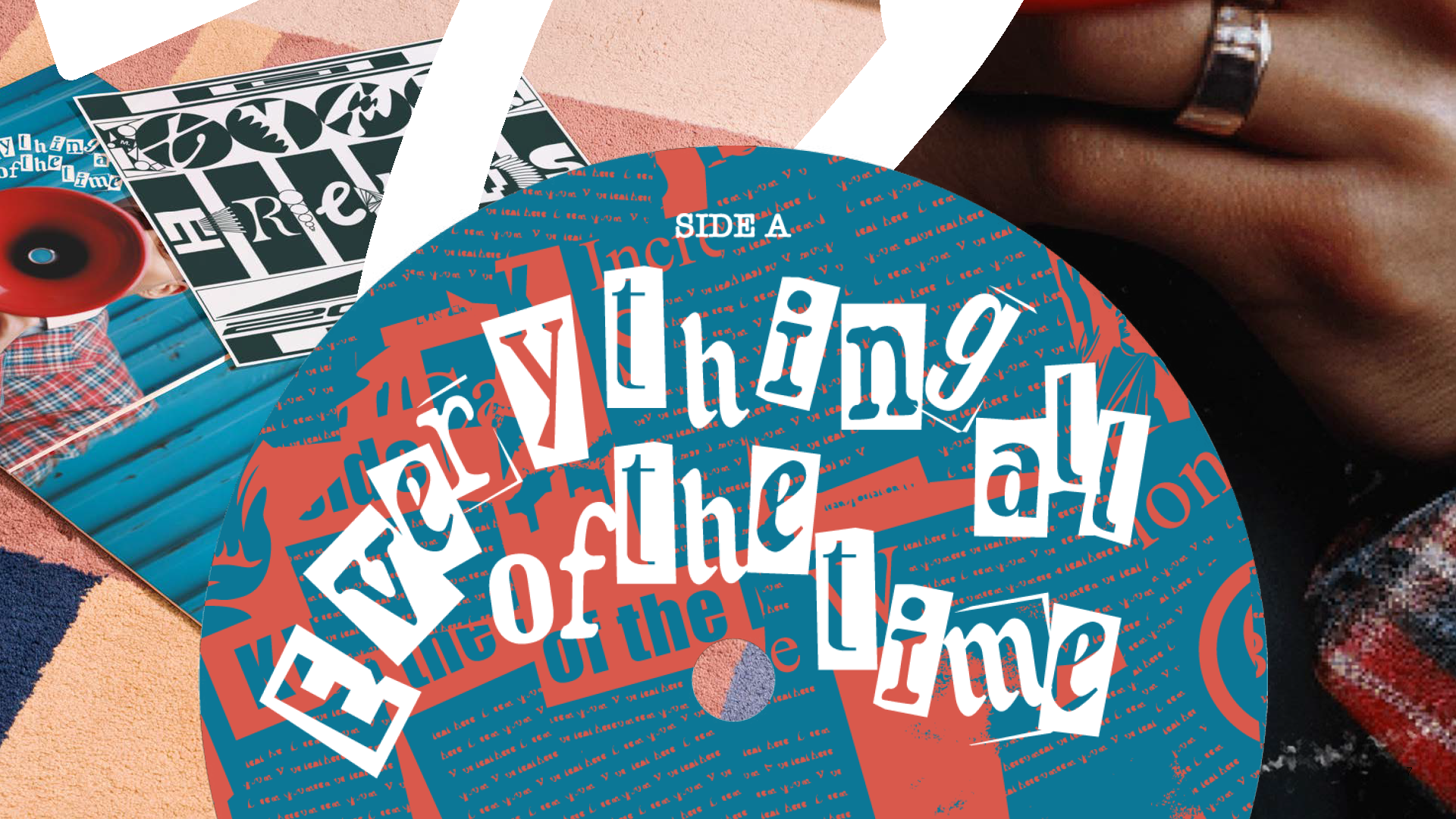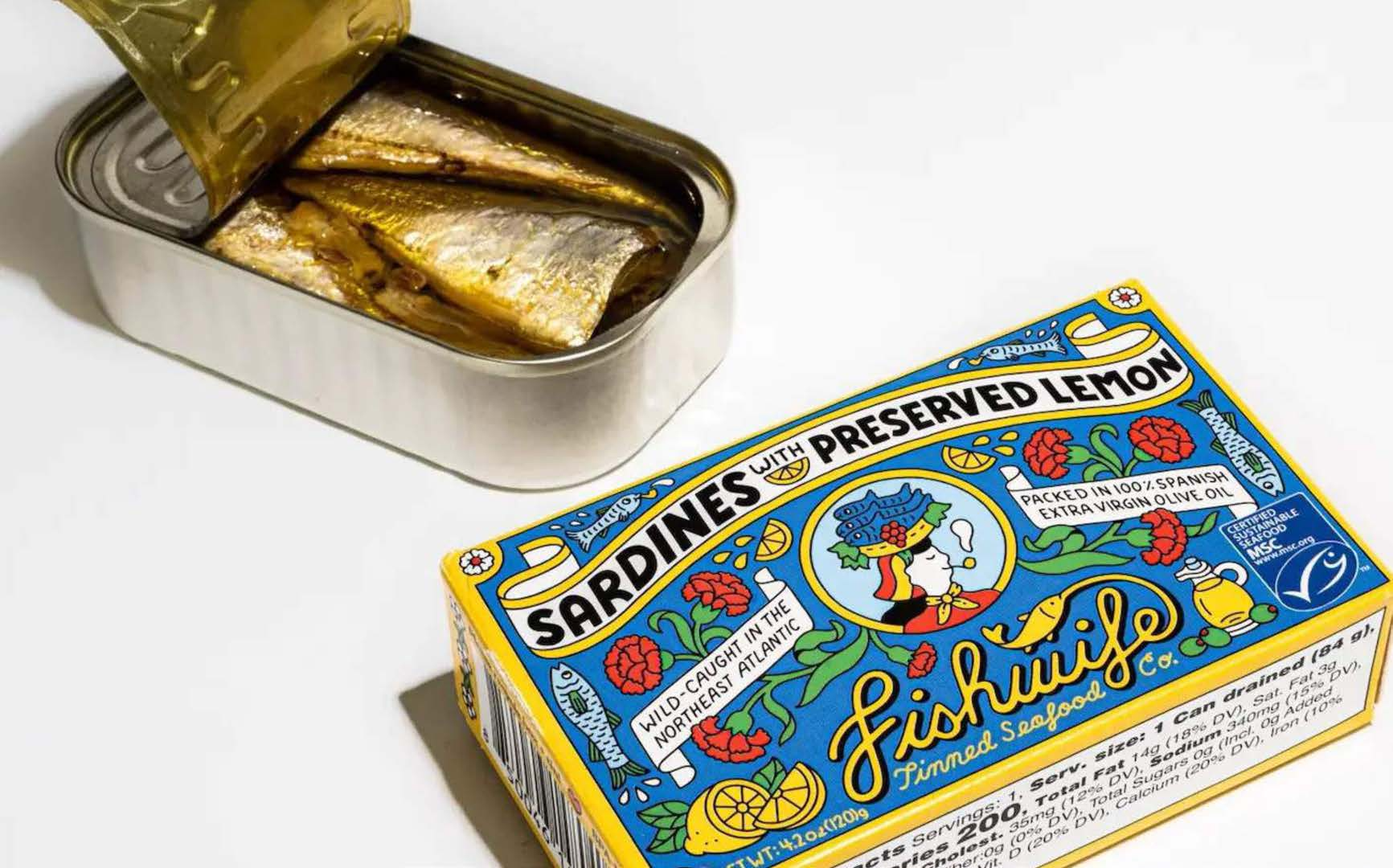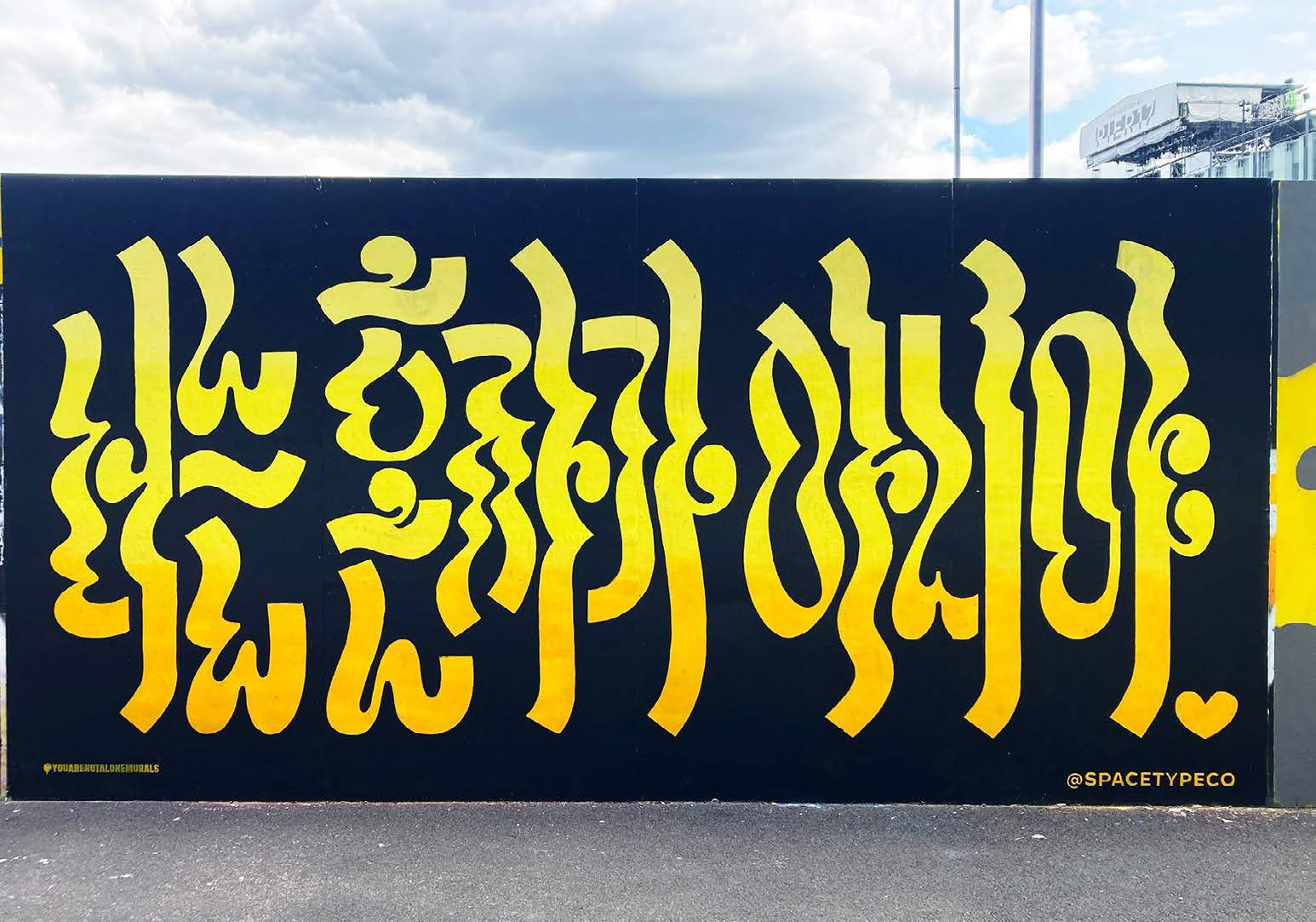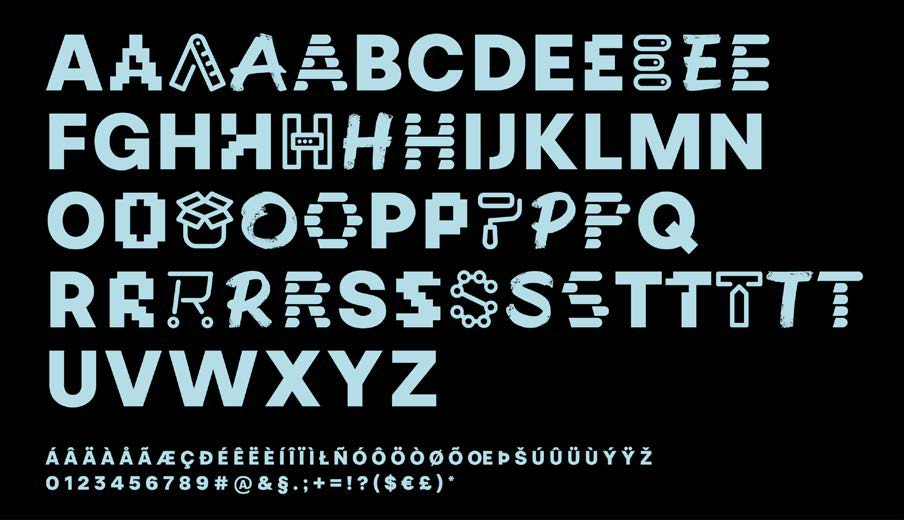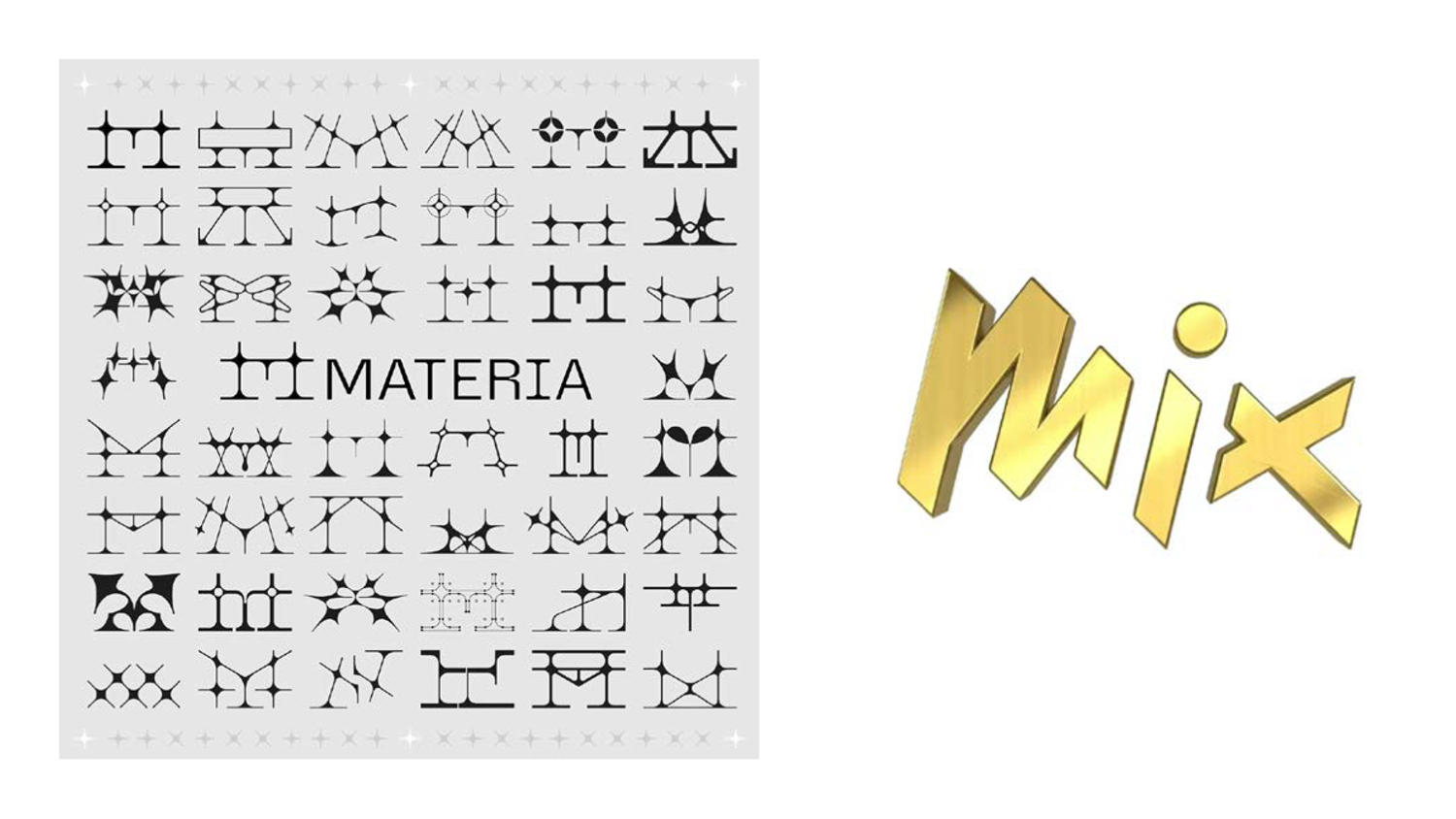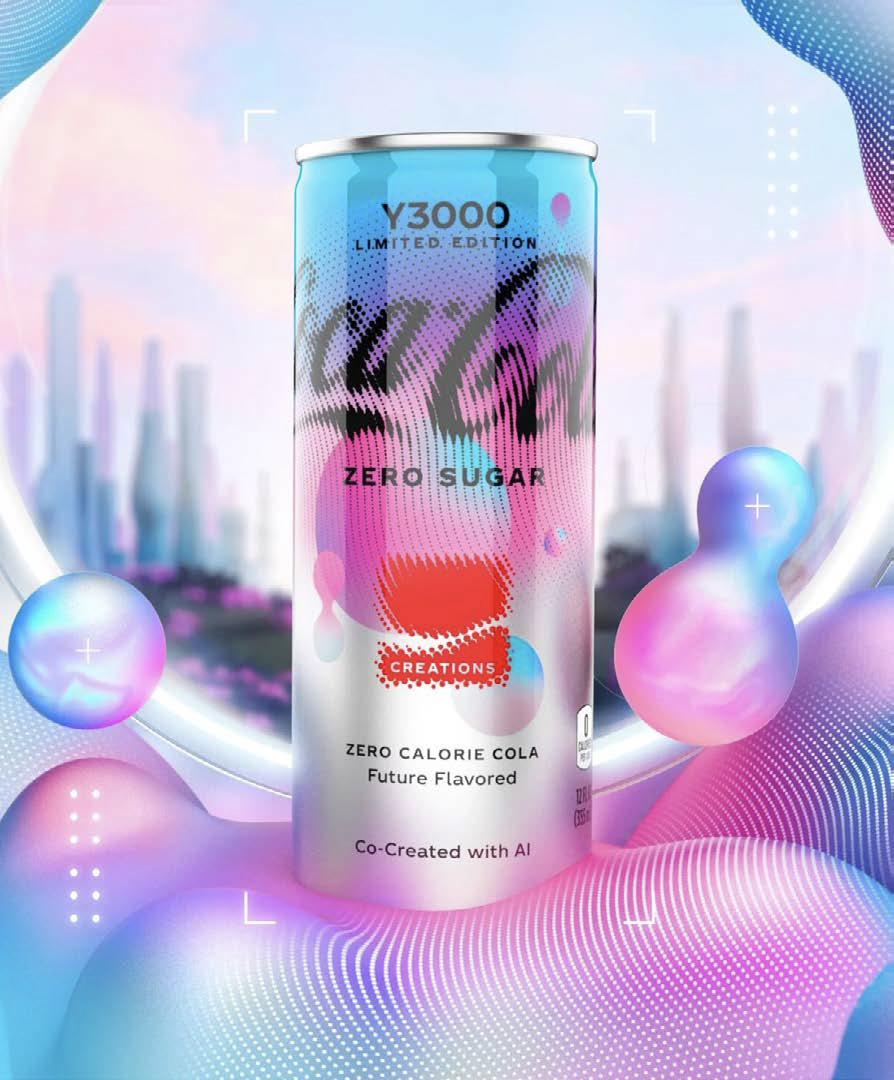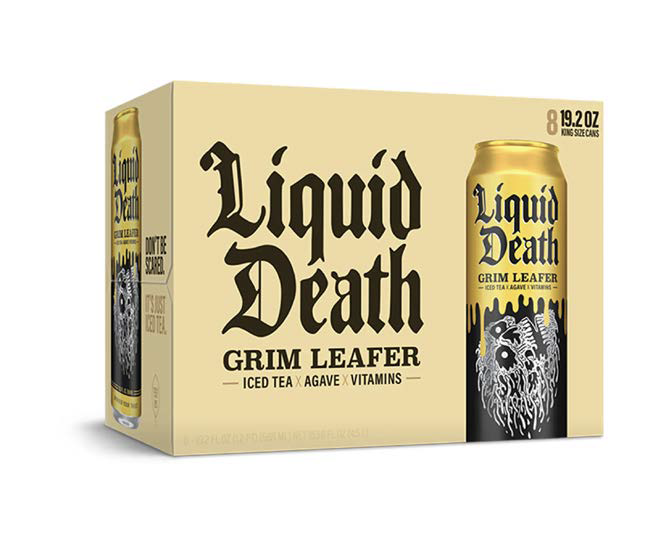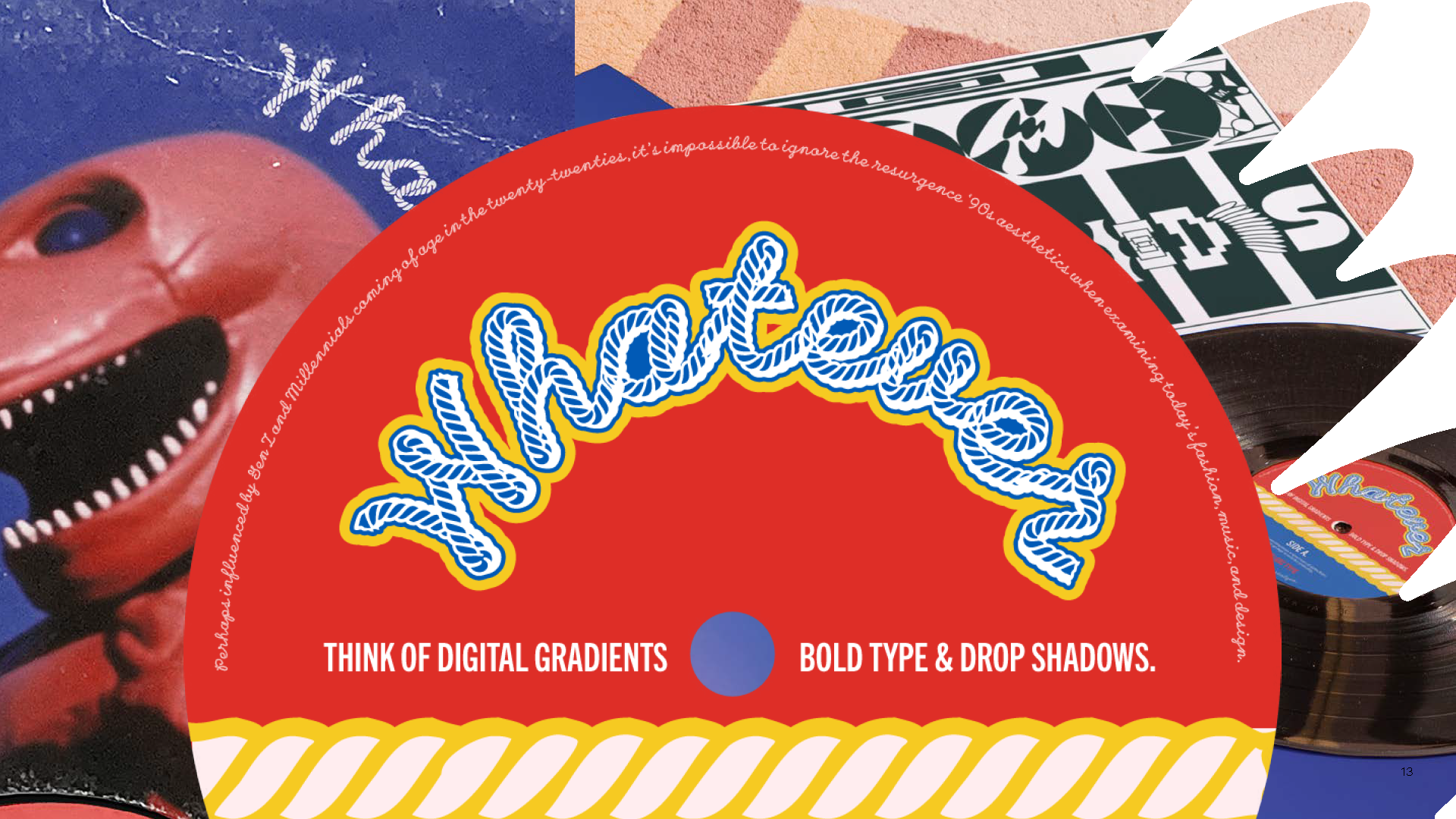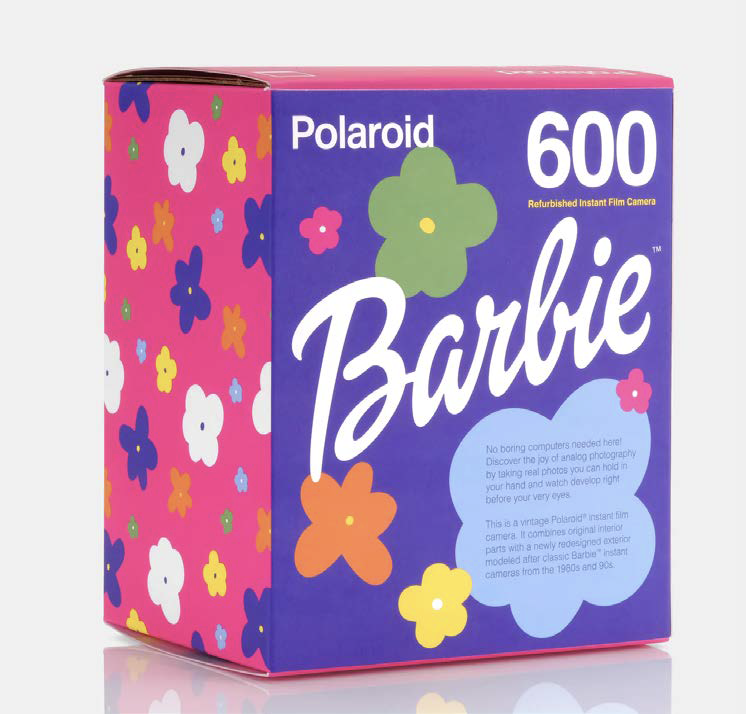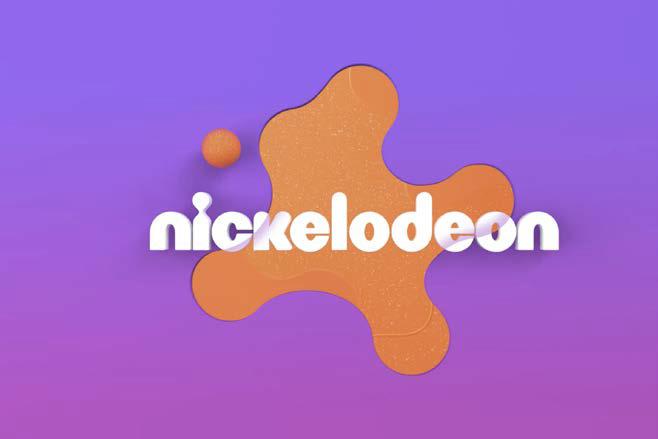
2024 新春之际,蒙纳面向全球正式发布《2024 年度字体趋势报告》。
本年度报告紧随过去一年里 AI 技术与设计的碰撞视角,亦关照复古美学与传统元素的回潮,捕捉错综复杂的当下,品牌与创意人士不约而同的表达诉求。
10 张由 Midjourney AI 共创的黑胶唱片封面,诠释 10 大字体趋势;60+ 全球年度先锋设计作品,涵盖从独立工作室到知名设计机构,从新锐品牌到老牌企业,令人惊艳的设计实践和应用场景。
黑胶唱片的视觉语言已经广受大众认可,而今年的趋势报告灵感也正源于此。在黑胶唱片封套经典的设计风格基础之上,这份趋势报告还融入了“摇滚”、“重金属”、“嘻哈”、“乡村”和“电子”等大众熟悉的音乐流派,并与字体中的不同风格联系起来。今年的趋势报告将涵盖更广泛的受众,提炼 10 个字体趋势,并辅以相关的研究与洞察详细阐述。
此次报告将字体置于音乐这一通用的场景,在创意人士和大众之间构建桥梁。在视觉上,我们借用熟悉的音乐流派,与不同的字体趋势建立视觉上的关联,通过丰富的配图,体现趋势背后的文化动因。
1 包罗万象 EVERYTHINGALLOFTHETIME.
如果说字体诉说了关乎当下世界的信息,那么此趋势便是一气呵成地反映了生活的方方面面。这一标题灵感来源于美国喜剧演员、音乐家和电影制片人 Bo Burnham 颇具调侃语调的歌曲《欢迎来到互联网》。这首歌以喜剧的方式展现了现代场景下的信息爆炸,以及令人沉溺却也兴奋的新兴网络世界。
Fishwife 是一个女性创办的食品品牌,专注于为消费者提供来源更有保障的优质即食鱼罐头。最近,该品牌推出了一款腌柠檬辣沙丁鱼新品罐头,其包装完美诠释了“包罗万象”的极致美学。设计师 Danny Miller 融合矢量插画、复古摄影、活泼色调、时髦字母与温情字体,创造出天马行空的包装设计,赋予罐头“秀色可餐”的视觉魅力。
Lynne Yun 为公共艺术项目“你并不孤单”创作了一幅壁画,该项目旨在激发人们对心理健康的关注。Lynne 用富有表现力的韩文字母进行绘制,向途经曼哈顿下城海港的韩语使用者们传递友好之意。壁画以鲜明的黄色、橙色和粉色为主色调,曲线优美,充满趣味性与实验性,并加以 Beatriz Lozano 制作的三维和图像识别 AR 扩展,使得色彩能够如键盘按键那样交替变换。
法国先锋设计公司 Lonsdale 为欧洲和拉丁美洲领先的开源电子商务解决方案提供商 Parisian Prestashop 设计了品牌形象,并以定制字体 Prestafont 为核心。新字体涵盖 4 款不同的字体家族,即像素字体、毛笔字体、图形字体以及装饰性无衬线体。这些字形基于核心的无衬线体演化而成,以反映 Parisian Prestashop 商家资源的丰富度及软件服务的自由度。每款字体风格都颇有意趣,混排时更是别开生面,与柔和淡雅的色彩相得益彰,展现字体排印的无限魅力。
如何才能真实地捕捉到物理空间的多面性?Materia(一家数字艺术画廊)和 Mix Brussels(一家集酒店、健身房、协同办公空间于一体的场所品牌)的徽标都以“包罗万象”的手法反映了空间的多面性。
总部位于巴黎的创意工作室 Golgotha 为 Materia 设计的徽标赋予了字母 M 48 种装饰变体。同样,Base Design 为 Mix 设计的形象也从 60 年代建筑中汲取灵感,以不同质感暗示 Mix 能够为用户提供多功能的空间。这两种非常规的设计方式都展示出设计师在探索徽标的极限 —— 既然标识可以包含多种元素,自然可以容纳更多表达。
在这一趋势中,还有两个饮料品牌案例值得一提。首先是拥有百年历史、广受认可的全球标杆性品牌可口可乐。可口可乐的最新限量版口味 Y3000 “能让人尝到未来”,因此团队利用 AIGC 共创包装设计,用流动的液点组成可口可乐标志性的斯宾塞体 logo,以“代表这颗星球未来的人类联系”。
在创意过程中借力 AI,是否能够比仅依靠人类创造出更惊艳的结果?你大概有自己的思考和回答,但同时也可以留意这样一个关键:这类案例不仅反映了某种设计趋势,也在启发更多相似实践。AI 所生成的复杂图案,也在推动设计师们创造更天马行空的作品。
相对于可口可乐,Liquid Death 是个更为新锐的罐装水品牌。从“MURDER YOUR THIRST”的标语到金属风格的骷髅头元素,这一品牌在营销和品牌塑造上都采用了自由不羁的风格。创意副总裁 Andy Pearson 表示:“Liquid Death 是许多有趣事物的混合体,比如重型音乐、黑色幽默、讽刺艺术等等。”还有什么比这更为“包罗万象”呢?
2 随心所欲 Whatever.
第二个字体流行趋势源于 90 年代的怀旧风潮,同“包罗万象”一样,该趋势涵盖了从垃圾摇滚到多彩像素等各种风格。渐变色彩、粗体大字、字体阴影……或许是受到 Z 世代及“千禧一代”的影响,在审视当今的时尚、音乐和设计时,我们无法忽视 90 年代美学的复苏。
2023 年 7 月上映的《芭比》,为这一年增添了许多桃红色与霓虹灯的 90 年代时尚元素。无数品牌与芭比跨界合作,希望借助这部年度票房大片获得热度。来自密尔沃基的产品设计工作室 Retrospekt 推出了芭比主题的宝丽来 600 拍立得相机,汲取上世纪 80 和 90 年代标志性的芭比元素,顺应了千禧一代的怀旧浪潮,为拍立得相机本身注入了更多的乐趣。
设计工作室 Roger 为尼克国际儿童频道更新的徽标,便是以理解孩子们的奇思妙想为核心概念,通过全新的形状和色彩,重塑标志性的粘液标志。该徽标采用了 ROC Grotesk 字体,并与 Neue Plak 字体搭配,在俏皮和凝练之间取得了平衡。
另一个深受孩子们喜爱的品牌是 Jell-O 果冻,知名品牌设计公司 Brand Opus 帮助其进行了十年来的首次品牌重塑。此次视觉更新以字体为核心,使用了圆润厚重的无衬线体,并刻意将较宽的字体 O 略微抬高,旨在以前卫的字体风格,唤起消费者的愉悦联想。改版后的徽标带有白色阴影,应用在带有鲜明卡通图案的包装上,也格外清晰。
英国伦敦知名广告公司 VCCP 与裸眼立体画出版商 Magic Eye Inc® 合作,通过创作一系列神秘的视错觉艺术品,帮助酸奶品牌 Müller Corner 焕发生机。“从时尚服鞋,到 Instagram 滤镜和 Tiktok 趋势,90 年代美学正在风靡。”Müller 战略和营销总监 Toby Bevans 表示,“消费者调研启发我们,重新推出过去广受青睐和怀念的密西西比棉花糖派口味,或许能帮助品牌在挖掘传统方面大有作为。”
是什么让“随心所欲”成为了甜点品牌的流行趋势?也许是我们从甜食中所体验到的舒适,让我们回想起孩童般的快乐与温暖。位于纽约的设计工作室 Safari Sundays 邀请字体厂商 Grilli Type 协助开发了一款名为 SWERVE 的标题字体,为 7-11 便利店的思乐冰(Slurpee,一款碎冰饮品)增添了新意。此外,它们还推出了吉祥物“Styles”,这个吉祥物由字母 S 组成,并与甜品的形状相匹配,从而彰显每个人心中所深藏的孩子气。霓虹色调、格纹图案、 全新标语……这些新鲜的声音帮助品牌与 Z 时代和千禧一代的年轻受众建立起更紧密的联系。
3 井然有序 SYSTM.
如果说“包罗万象”反映的是现代生活中的错综复杂,那么“井然有序“则回归结构、控制和精确,让人得以短暂喘息。
位于阿姆斯特丹的设计工作室 WONDERLAND 的执行创意总监 Martijn van der Does 将其称为“慢设计”。他表示:“我们由技术驱动的快节奏世界重视速度和效率,而慢设计则与之对抗,倡导一种更深思熟虑的方式。”它鼓励我们与使用的产品和居住的环境建立更深层次的联系,从而对抗快速消费文化。
在过去的几年中,模块化、机械化和工业化的字体变得更为温暖细腻。“井然有序“延续了该趋势,同时更强调“亲身参与”的理念。尽管设计字母有着既定方法,但本趋势所涵盖的设计实践,以更柔和的形式、更周到的考虑,增强了人性化因素。
“我们创造简单易安装的高级设计。”
阿姆斯特丹建筑产品制造商 Nown 的标语完全彰显了“井然有序”的精髓。该企业的视觉形象由巴黎设计公司 Brand Brothers 负责,采用了较宽的定制徽标,强调锐利而重复的角度,以及各段之间的连接细节,与他们生产制造的碳中和建筑产品相呼应。搭配的字体为 Lineto 的 Replica,且大多应用的是大写字母。
下面,让我们来看一看英国曼彻斯特博物馆更新后的南亚展厅。独立设计师 Sthuthi Ramesh 与字体厂商 Universal Thirst 合作设计了 SAG Stencil 字体,旨在捕捉从南亚到曼彻斯特沿途旅程的精髓。SAG Stencil 采用了模块化字体,横跨孟加拉文、天城文、古吉拉特文、果鲁穆奇文、拉丁文、泰米尔文和乌尔都文共七种文字。这款定制字体的灵感来源于古吉拉特活字印刷厂 1937 年的字体样张,以及在印度火车站发现的手工标牌,从而赋予展厅历史感和创造力。
另一个关于“井然有序”的案例或许会让你意想不到,来源于啤酒品牌 Molson Coors。芝加哥 DDB 广告公司为 Coors Light 设计的凉爽屋檐(chillboards)屡获殊荣,利用字体排印为佛罗里达州迈阿密的一个社区降温。团队邀请当地街头艺术家 Andaluz 协助设计了一款定制字体,在屋顶上使用了高反光的白色油漆涂上该标语,覆盖面积达 96%,从而帮助居民节省水电费,并提高对气候变化的认知。更酷的是,作为此次营销活动的一环,Molson Coors 还将送出 5000 加仑反光白漆。
接下来是耐克的 CURV Studios 字标案例,由著名广告公司 AKQA 设计,代表着创意的四个阶段,即准备、孵化、启示和验证。每个字母都被框定在气泡状的 4×4 网格中,在不同比例下都非常清晰。与之搭配的 swoosh 标志,灵感来源于耐克的创新文化,也被分割为 4 个部分,与创意的各个阶段匹配。
最后一个案例来自于平面设计工作室 Workbyworks 为街头服饰品牌 BONELESS 设计的标识,该品牌致力于为年轻一代提供高品质且价格合理的服饰。设计以宽比例的字母 B 为核心,采用 3×5 的灵活网格结构,为徽标和布局系统奠定了基础。
4 重塑结构 De-form.
这是一款举世惊艳的可变字体,抑或只是有些“变形”?如果将画面上所有可能的像素都填满,又会是什么效果?
不同于“井然有序”,“重塑结构”打破了字体的骨架,渴望占据更大的画面版块,将字体的可能性无限延展。这一趋势下的字体们在不同的状态间摇摆变形,既端正又柔软,却很少介于中庸状态,而是呈现强烈的视觉冲击力。
该趋势也正促使设计师们尝试过往几十年来不被提倡的变形方法。“重塑结构”的设计不再严格遵循字重平衡、宽度一致、字形比例,而是享受更多实验乐趣。
这一趋势是否是在对抗保守的同质化设计和过度简洁的技术美学?或许暗流涌动的全球文化和社会问题(如战争、政治极端主义、通货膨胀、罢工和生活成本问题)正在引发美学的反叛。设计师们是否潜意识中吸收了这些情绪,并反映到了作品中?也许我们需要打破因循守旧的规则,表达更多共同经历的当下。
设计工作室 Kiln 受委托为英国皇家电视学会(Royal Television Society)的剑桥大会设计标识,旨在突出学会“太多可看(Too Much to Watch)”的主题,同时避免让人感到悲观或焦虑。
徽标采用了色彩丰富、充满张力的气泡字母,字母排列紧密,仿佛在争夺着空间,与当下不断涌现的内容争抢着注意力相呼应。设计团队利用定制的渲染技术随机操纵字母形状,从而通过基于物理模拟的复杂动态设计增强了该效果。
美国服饰品牌 American Apparel 以其极简美学而闻名,与设计公司 LG2 Architecture 合作,在时尚展会中打造了类似博物馆的体验,以宣传其经典的 Black 2001 T 恤。参与者沿着引导路径进入一个离地 4 英尺,16 英尺高的黑色箱体;在里面,他们会体验 7 个展示经典 Black 2001 T 恤特性的装置。箱体表面的字体尺寸巨大,并拉伸扭曲到极端比例,视觉效果上却恰到好处、协调一致,与令人印象深刻的快闪展览形式相得益彰。
Detroit 是位于巴黎的一家创意机构,代表了一批国际人工智能艺术家,从事传播、新闻和文化领域的工作。徽标基于 Acumin Extra Condensed 字体,旨在强调“Detroit”这一机构名,以及人类和机器间的羁绊概念;结构的变形则是呈现了人工智能凭借其无限可能性而引起的眩晕感。
瑞典风景宜人的达拉纳地区,以旅游业以及铜矿开采、骑马、越野滑雪等传统行业而闻名;但该地区也是一些全球高科技企业的所在地,需要吸引年轻的员工。因此,斯德哥尔摩设计公司 Soderhavet 与 Placebrander 合作,为达拉纳地区打造全新品牌形象,突出发展前景。定制完成的标题字体,美学灵感源于丰富的文化要素,外形敦实而具张力,仅用一个字母或是一个单词,再加上遮罩图像,便能成为传达品牌故事的窗口。
设计工作室 &Form 为东京巨蛋城设计的徽标业采用了类似的思路,利用与大曲都市(Toshi Omagari)共同开发的定制软件,使可变字体可以在不同形状和颜色之间变化,从而展现该设施所提供服务的多样化。
全球知名的设计公司 Pentagram 为拥有 148 年历史的英国百货品牌 Liberty Fabrics 独家设计了包袋和围巾胶囊系列。为了传达其“毫不掩饰的古怪”的品牌理念,Pentagram 与字体公司 Colophon 合作定制了 Lasenby Sans 字体。这是一款人文主义字体,灵感提炼于 Liberty 悬挂于大马尔伯勒街入口处的招牌字样。设计团队利用这款字体玩转排版设计,将传统风格与现代技术相结合,创造出了大胆的万花筒纹样。
5 流动 Flux.
“流动”或许可以算作“重塑结构”下的细分类别之一,也是过去几年逐渐流行起来的趋势。无论是真正的动画还是仅从动态中获取灵感,“流动”都充满速度与活力。你或许还会发现利用人工智能创造动态和交互的字体。以下相关的创意项目都关乎品牌重塑,其中还包含了两个强调转变与速度的体育品牌。
首先是全球知名的设计公司 Pentagram 的另一个代表案例。他们与设计工作室 Nomad 和创意咨询公司 Heavenly 共同合作,为伦敦自然史博物馆进行品牌重塑,传达出力量与活力。升级后品牌形象的核心是从内向外扩散的环形字母,象征博物馆积极推动地球自然环保。定制字体 NHM Wallop 基于字体公司 Displaay Type 旗下的无衬线体 Wallop,也在排版中应用到了环状结构。设计团队制作了一个生成器,可以通过编码创建静态和动态输出,使任何与博物馆合作的设计者都能够轻松兼顾一致性和灵活性。
“这些元素能够运动、生长、扩展和变形,以动态的方式进行交流,为品牌注入令人难忘的活力。”
为加强与意大利城市的紧密联系,全球知名的品牌设计机构朗涛(Landor)协助意大利最重要的交响乐团之一 LaVerdi 进行品牌重塑,更名为“米兰交响乐团”,并从通感(synesthesia)这一概念中汲取灵感,定制了颇为前卫的字体 TUMB TUMB,构成徽标的核心。
“徽标能够根据乐团演奏的强度而变宽或变窄”,在视觉上回溯了 20 世纪早期艺术作品风格,为整个乐团形象注入了活力与能量。
现在让我们把目光从艺术转向游戏行业。英国创意公司 Uncommon 将热门足球游戏《FIFA》系列更名为《EA Sports FC》,并使用了全新的三角品牌标志,这一形状来源于游戏中玩家角色上方浮动的三角形。Uncommon 还与字体厂商 F37 合作,从两位传奇足球运动员约翰·克鲁伊夫(Johan Cruyff)和玛塔(Marta)身上汲取灵感,定制了两款字体。一款字体将克鲁伊夫的风格融入到字干的结构设计中,在三角形元素中加入了油墨陷阱(ink trap),而另一款字体则彰显了巴西足球运动员玛塔的风格和天赋。
设计机构 DesignStudio 在重塑广受欢迎的德国多特蒙德足球俱乐部(Borussia Dortmund,简称 BVB)品牌形象时,采用了现代与经典兼顾的方法,在尊重其丰富传统的同时,还引入了富有速度感的可变字体和标志。团队与字体公司 Blaze Type 合作,设计了一款定制字体,与多特蒙德主场西格纳尔·伊杜纳公园球场站台 34º 锐角相呼应。可变字体的形式彰显了多特蒙德厚积薄发的体育精神,标题字体增加了独特的“强度字符”,并与功能性的正文字体相平衡。升级后的品牌形象捕捉到了 BVB 的精神根源,与球队标志性的黑黄色调相搭配,传达了球队强大的生命力和联结力。
众筹贷款平台 Bankers 横跨半个地球,进入日本市场,并在大约 30 个月的时间里累计获得 200 亿日元的投资,堪称“业内最快”。为了与其快速发展相匹配,Bankers 在东京地区火车站的品牌广告中采用了质感强烈、渐变丰富的插图,并搭配看起来像是用软头钢笔快速书写而成的字体,传达出惊艳与快速的能量,彰显品牌活力。
6 怪诞 Quirk.
所谓“怪诞”(Quirk),顾名思义,指的是利用一些显眼特征来吸引客户眼球的字体。毕竟,品牌推广就是需要一定的激进思考:愿意尝试一些意想不到的事物,特立独行。然而,这种“与众不同”似乎与客户的“舒适度”存在一些冲突。 这种冲突,催生了许多“怪诞”创新:利用一些别具匠心小设计, 在符合整体视觉规范的前提下,带来一丝松弛感。这一趋势,强调的是“舒适度”和“视觉张力”之间的平衡,那些小小的怪诞设计,像是藏在普通的无衬线背后,对你抛媚眼。
廉价航空公司 Scott 's Cheap Flights 更名为 Going 之后,DesignStudio 为其重新设计了字标,使其更具表现力和趣味性,也彰显了 Going 在旅游行业的重要地位。新的字标呼应了旅途中的意外之喜,字母 G 顶部的小圈让笔画方向自然向下,象征品牌一直秉承的低价理念和极致性价比。字标中字母皆以斜体呈现,字母 G 以箭头收尾,更加凸显了力量感。配色的灵感源于全球的生物多样性,箭头还模拟了地球自转方向,也寓意着跨越长距离的旅途。充满冒险精神与好奇心的旅程,这也是 Going 的愿景。
“用一首特别定制的歌曲,点亮别人的世界”,这是 Songlit 平台的理念。其品牌的定制字体也体现了音乐本身流动顺滑的意象。Songlit 的品牌设计由 Australian Studio Work 完成,结合了 Dinamo 字体公司的 Maxi Plus Variable 和 Repro 字体。新的品牌包含了大量的插画元素,色彩明亮,体现了平台无尽的定制化可能性。
Wisl 被称为“本地体育引擎”,用户可以找到有共同兴趣的运动搭档。来自立陶宛的设计公司 andstudio 为其定制了字标,其中的字母 W 成为了品牌代表性的元素,彰显玩趣与亲和力。手绘插图、图标、弹力球,让品牌形象鲜活有力,与运动的激情产生关联。
宠物护理品牌 FLOOF 的徽标和品牌形象由纽约创意机构 SMAKK 完成,其设计运用了类似的手法。 FLOOF 旨在为狗狗提供从头到尾的护理。徽标中字母 L 的设计带着些许俏皮,品牌使用的正文字体又更加冷静,体现了护理产品的科学配方,两者结合可谓相得益彰。
法国创意机构 Graphéine 为巴黎第二十区打造了全新的形象。“此次的设计目标是比原有的徽标更加紧凑,同时结合象征性元素,表现这个区的独有特征。”法语中“第二十”的单词是 Vingtième,Graphéine 巧妙地将字母 g 融入了设计,旋转九十度后,就有了双重含义。此外,标志也隐喻了该区的地形,象征巴黎城市的最高点 。
2024 年奥运会将在巴黎举行。W&Cie 从上世纪 20 年代获取灵感,采用灵活、简约的处理手法,传承巴黎的奥运历史。活泼的配色与城市的石质面貌构成和谐对比。字体设计师 Julie Soudanne 和 Elliot Amblard 为此次奥运会制作了一套定制字体,灵感源于装饰艺术运动,致敬 1924 年巴黎奥运会。这套字体由 7 个字重组成,包含替换字符、斜体以及可变版本,以现代的手法体现复古美学。
“怪诞”的无衬线体出现在此次趋势报告中,算是实至名归,就连老牌创意机构 Wolff Olins 的品牌更新也拥抱了这种风格。过去近 60 年, Wolff Olins 塑造了一系列知名品牌,包括:联合利华、强生、谷歌、爱彼迎和英国国家医疗服务体系(NHS)。字标中的字母 W 让整体耳目一新:线条蜿蜒扭曲,甚至还有一丝迷幻,与简洁的无衬线构成对比。Wolff Olins 的新闻稿中写道:“(W 的形状)代表了我们的核心价值,注重过程;也是企业文化的体现,每个人都可以表达个性,锋芒毕露,释放创造力,为我们的客户制造更多可能性。”
7 负空间“反”击 Counter Attack.
上文提到的“怪诞”,做的是加法,让文字看起来更有味道。但这里的“反击”(Counter Attack)做的是减法,借用非现实元素,实现同样的目的。这一趋势下,负空间成为主角。这种字母的处理方式让造型内部呈现出特殊的视觉愉悦感,也传达出一种更复杂的技术感。
1930年,德国书法家、排版师和图书设计师 Jan Tschichold 写道:“白色空间应该被视作一种活跃的元素,而不是被动的背景。”这里提到的趋势也呼应了这一说法。某种程度上,白色空间成为了视觉焦点的主要元素。设计师在字母间的空隙里大做文章,像不像室内设计师?
非盈利组织 Building Diversity 致力于提升全球建筑的多样性和包容性。创意机构 Danish Public Service Group “专注于为非破坏性品牌和组织服务”,为 Building Diversity 打造了简洁有趣的品牌形象。所有的排版都基于网格,并且选用了来自 Lift Type 的 Baste 字体。字体独有的形状贯穿整套视觉系统。和其相配的衬线字体是由 Margot Lévêque 设计的 Kalice,为整体风格融入高级感的曲线和亲和力。
伦敦码头区博物馆位于伦敦东区,这是一片后工业景观,和其相映成趣的是“以玻璃塔和单轨电车为背景,历经百年的基础设施、工业设备和仓库。出于地段考虑,Studio Bergini 选用了来自 David Jonathan Ross(DJR)的 Megazoid 字体,用于其徽标和品牌视觉体系,使用锐利的角度和圈圈对齐修饰。结合 20 世纪中叶拍摄于东伦敦的双色调照片,该作品巧妙地反映了东区及其码头区的景致、人文和历史风貌。
总部位于西贡的品牌工作室M-N Associates 仔细研究了艺术家 Vũ Thắng 的陶瓷技艺,并与字体设计师 Tra Giang 合作,将形状融入到定制字体 MN Vũ Thắng ,勾勒出形似“陶器—鞋履—心灵”的油墨陷印(inktraps),构成完整的字体视觉体系。
RATIO 创新园区在加州 Emeryville 启动后,创意机构 Landscape 为其开展全面的品牌推广活动,包括全新的品牌形象、数字体验和标识系统。这些精心打造都彰显着园区的朝气蓬勃。RATIO 字标基于 Monument Grotesk 字体(来自Dinamo字体公司),Landscape 对其进行重绘,融入有机形状。
Eames Institute of Infinite Curiosity(无限好奇研究所) 全新的品牌形象由来自旧金山的创意机构 Manual 打造。小写字母 e 被玩出了花,代表了研究所的好奇精神。Manual深入研究了Eames Ranch的资料,仔细研究了收藏品和个人档案,最终确定了明亮、现代的品牌形象。这个设计也让人联想到了诺尔泽立方体(如果感觉陌生,可以阅读 Gerrit Noordzij 撰写的 The Stroke: Theory of Writing)。
回到实体产品,我们也找到了一些有趣且充满怀旧情调的设计。Blum Skincare 的包装也体现了品牌的使:提升消费者的自然美。Blum 欢快、色彩丰富的包装由 Lina Aragon 和María Alejandra Maya-Fresa 设计。厚实的标志上刻有嫩芽一般的形状,并出现在极简包装上,留有大量负空间,让标志散发出温暖而愉悦。
Frekl 是一款无酒精姜汁啤酒,主打“愉快、无负罪感”,再现经典,实现健康活力的生活方式。 Electric Brands 打造的全套形象将生动的信息以大胆的字体呈现,并结合奇特的几何形状,“以更健康的方式给你的味蕾带来一丝怀旧”。
在西部片时代,牛仔们喝什么咖啡来保持精力充沛的?这正是 Seachange 在为 LOOT Coffee 打造品牌形象时想到的问题,LOOT Coffee 是一款新型的特色咖啡,在干旱、多尘的澳大利亚西部完成烘焙。字标让人联想到“通缉”海报:字体融入了厚实的衬线,锐利的尖刺,还有枪支的形状。创意文案、巧妙的包装和标识完美地衬托了此项品牌设计作品的精湛之处,让 LOOT 在澳大利亚竞争激烈的咖啡烘焙商中脱颖而出。
8 不加修饰 PROFESHINAL.
这一趋势看似简单,实则饱含坦率,为繁复精致的视觉景观注入了一股冷静的视角。如果说平面设计追求完美的创作,那么“不加修饰”则是毫无保留地展现出真实设计。
探索这一趋势的设计师们聚焦作品的简约之美。人们常说“没有比孩子更诚实的人”,或许这正是该趋势的核心。对简单事物的敏锐鉴赏力,对幽默与真诚的巧妙融合,造就了充满好奇又才华横溢的作品。正如毕加索的名言那样,“我花了四年时间画得像拉斐尔一样,但用一生的时间,才能像孩子一样画画。”
这在 Radford Beauty 最近的品牌焕新案例中尤为明显。品牌期望视觉形象与他们的核心理念相契合:缓解美容行业的“过载”现状,成为一家重视产品胜过包装的公司。新的设计由来自洛杉矶的 Day Job 公司完成,简约风格强调了内在而不是包装。手绘字体和图形增添了一丝趣味和轻盈感,在一个充满各种“过载”的领域,成为一股“简单又直接”的清流。这种简单而俏皮的外观体现了“不加修饰”的精髓。
设计师 Frith Kerr 为位于伦敦北部的面包店 Jolene 创作的作品也呈现了朴质简约的设计风格。徽标以 Kerr 六岁儿子的手绘字体为基础,呼应了 Jolene 的可持续价值观。
这股趋势象征着品牌能够自如地展现真实面貌,无需矫揉造作,便能展现趣味,从各类品牌中脱颖而出。
烹饪品牌百福(Momofuku)为其居家产品所进行的全新设计也可圈可点。其设计灵感来自餐厅的核心组成部分,即厨房、散客与储藏室。百福出品的酱油、芝麻酱和芝麻油灌装在简单的琥珀色瓶子中,暗示了其带来美味的“秘方”。每件产品都贴有胶带状标签,以简明的手写体标注了产品内容,干面条的包装也采用了相同的设计。
百福的设计总监 Brendan Newell 解释道:“制作标签的过程非常简单,用锋利的笔反复书写,直到每个单词在易认性和手写感之间取得适当平衡。”世界各地的餐厅厨房都会使用美纹纸胶带来标记内容物,而将其作为包装设计的关键元素,不仅突出了调味料的故事,还传达了它与厨房本身的密切关系。
法国平面设计公司 Graphéine 为护理管理平台开发商 MadeForMed 进行的品牌重塑也彰显了同样的理念。设计团队捕捉到了大多数医生显著的共性之一,即难以辨认的笔迹,并将其作为品牌形象的核心元素。由于 MadeForMed 就是基于医生使用而设计的,因此其徽标的含义就是要展现有些古怪的趣味,呈现人的“真实感”。
“不加修饰”也通过愉悦的视角,赋予了多元化设计许多可能性。柏林设计工作室 PFA 的新字体作品便是极佳的例证。Pardon 是一款“有意失败”的单一字重手写体。
“Pardon”这一命名本身便蕴含着幽默,虽是表达歉意的单词,但这款字体本身却相当坚持个性。创作者 Martin Aleith 说:“为了模仿手写的多样性,我们为每个字母开发了四款备选字体。我第一次为字母的创新进步感到如此愉悦。”
位于阿姆斯特丹的设计公司 Wonderland 为个人和专业辅导服务公司 Happy Fuel 设计的徽标也彰显了多样性。徽标中的每个字母都饱含不同的情绪,交织在一起,传达出变化的趣味。
另一款有趣的字体设计来自于 House of Gül 一份关于美国穆斯林年轻人如何庆祝斋月的报告,其外观灵感源自斋月期间的愉悦和爱意,并采用了定制的阿拉伯书法。
9 回归天然 100% Natural.
“回归天然”这一趋势含义丰富,是可持续品牌追求将自然元素融入视觉,表达对周围环境的呼唤以及对美好事物的承诺。同时,它也饱含着手作感,通过创作新鲜的设计,为品牌带来更多触点。被誉为“世界自然纪录片之父”,《地球脉动》、《蓝色星球》等知名纪录片的主持人大卫·爱登堡常说:“在我看来,自然界能给予人最深刻的战栗、最惊艳的美感与最丰富的智慧。许多让我们感到生命值得的事物,都来自于自然界。”
这一趋势揭示了我们所处的环境如何激发创作灵感,而触感和技艺又是怎样传达出质朴俏皮之感的。
越南宠物食品制造商 HiRaw 近期的品牌重塑便体现了“回归天然”的精髓。HiRaw 与创意设计公司 M — N Associates 合作,通过与众不同的品牌形象在竞争激烈的市场中脱颖而出。
围绕“提供美味生食(Raw for All)”的概念,捕捉宠物顽皮的活力,全新的品牌形象呈现出大胆有力、直率有趣的氛围。设计以有着朴质手工感的定制字体”MN RAW“为中心,将生鲜食品的质感融入其中。弧形的感叹号也为整体视觉增添了意趣,让人联想到享受着美食的宠物们不禁摇晃的尾巴。
位于英国贝尔法斯特的餐厅 Vero 主打健康饮食,其形象设计也体现了许多原初而自然的元素。Vero 的品牌视觉基于 NaN Juane 字体所构建的徽标,以柔和的大地色为基调,俏皮而大胆,表达了其为顾客提供温馨愉悦的环境和正宗天然食品的承诺。
“回归天然”强调手工,从自然环境中汲取灵感。这一点在 Big Country Organic Brewing 于 2023 年推出的全新品牌形象中体现得尤为明显。该品牌在推出三款啤酒新品时,邀请了设计公司 Land studio 为其更新视觉,基于地区风格来创作这几款啤酒的设计要素。包装以字体为核心,通过几款手写字体,让人联想到旧时的手绘标志。
Land studio 的联合创始人 Caleb Everitt 表示:“20 世纪 50 年代前的美国高速公路标识或是巷口招牌,几乎可以说是美国梦的无形语言。”三款新品包装的特定设计,能让人联想到德克萨斯州、新英格兰和加利福尼亚州的典型形象。例如,Tex-Mex Lager 这款啤酒就采用了阳光下的仙人掌元素,周围环绕着响尾蛇构成的拱门,象征着典型的德克萨斯州风貌。手写的字体和简单的图案,与品牌朴质大胆的风格相呼应。
益生菌苏打水品牌 Mayawell 的全新品牌形象也采用了类似的设计方法,既工艺精湛,又富环保意识。此次品牌重塑由墨西哥设计工作室 Heavy 负责,将阿兹特克神话和玛雅神话中的生物和大胆的手绘风格字体结合在一起,通过对历史要素的把玩,探索该品牌兼具德克萨斯州及墨西哥的传统风味。
谈到手工,还有什么比刺绣更巧夺天工?2023 年,广受喜爱的经典作品
The Girls’ Guide to Hunting and Fishing
再版。这本小说由已故的 Melissa Bank 创作,是一部环环相扣的短篇小说集,讲述了一位美国年轻女孩的成长故事。 Annie Atkins 为企鹅必读系列里的这本新版设计了封面,企鹅艺术总监 Saffron Stocker 担任艺术指导。设计灵感来源于女童子军的刺绣徽章,散发出自然怀旧的气息。
10 衬线复苏 Return of the Serif.
几十年来,设计界的简约风潮一直持续着,无衬线体占据人们的眼球。而在当下这个不安的时代,每个人都在与自己的冲突挣扎着,传统与经典也悄然复苏。怀旧既传达出端庄严肃的基调,又让人倍感轻松愉悦,让我们在日益复杂的环境中有所依靠。
在这一趋势中,一些品牌在致敬传统的同时也在展望未来,而另一些品牌则试图在极简外寻求更多。
让我们从漫步一座英式花园开始。Borde Hill 是一座拥有 400 年历史的英国乡村花园,亟待更新视觉形象,以面向更广泛的受众。设计机构 Here 负责品牌重塑工作,从大自然中汲取了许多设计灵感。例如,字母“i”的圆点是一粒种子,字符的宽度对比鲜明,暗示着不同植物并排生长。开阔的字怀增添了轻盈感,而短衬线则赋予现代性,作品整体充满隽永的传统感。
创意设计公司 Zoo 在巴黎奥赛博物馆的品牌重塑中也采用了类似的思路。该博物馆是巴黎城市风格的基石之一,也是一座能让历史瞬间鲜活起来的建筑。Zoo 设计了一款名为 Orsay Elzevir 的定制字体,它既要与现代观众产生联系,又要立足于博物馆的丰富历史和特定时期。Orsay Elzevir 字体注重易认性和清晰度,同时通过现代视角捕捉传统精髓,对旧时的美学进行了当代诠释。
与此类似的是,伦敦国家肖像馆也进行了形象升级,蒙纳为其定制开发了衬线字体 NPG Serif,呈现出传统与现代的完美平衡。
在无衬线字体占主导的设计领域,对个性的强烈渴望越发突出。为了脱颖而出,一些品牌出人意料,采取了回归传统的方式。
全球知名的品牌设计机构 Landor & Fitch 将品牌名更新为 Landor(朗涛),并定制了衬线体 Landor Sans,作为此次品牌重塑的基础。新视觉形象受到水的启发,与工作的流动性和适应性相呼应,Landor 希望其全新视觉形象能够传达出他们所能提供的一系列服务。“我们的新字标将现代衬线字体和微妙的设计细节相结合,传达庄重感的同时不失趣味性,也与泛滥的无衬线标识相区分。”
知名广告公司 MullenLowe Global 的品牌重塑也与 Landor 的实践异曲同工。灵感源于 MullenLowe 标志性的章鱼图样,在抽象轮廓的基础上不断演绎变化。这种不受拘束的设计方式与大胆时髦的衬线体相搭配,使得新标识既充满现代感,又不乏怀旧性,从而在赋予品牌统一标识的同时,为个性化留下空间。
一些品牌坚持其历史传统或追求与众不同,而美汁源则运用衬线体发出统一的品牌声音,并提升识别度。2023 年,美汁源首次在全球范围内重塑品牌形象,新外观展现了微妙的复古意蕴,延续了我们前几年所总结的“软衬线”字体趋势,同时也蕴含了 1945 年最初版徽标的色彩。美汁源在全球 100 多个国家以各种名称出现,如今统一的标识将更大程度地呈现其愉悦的品牌风格。
印度尼西亚美妆企业 Pinklab.Co 的品牌重塑也展现了对清晰形象的需求。该企业与设计机构 Widarto Impact 合作,围绕强调易认性的圆润衬线字体,简化了品牌视觉,拉近了与消费者的距离。
衬线字体的回归体现了其适应性、经典性和现代性,以及品牌能够利用衬线体寻求更多的个性。在未来的几年里,我们或许可以期待衬线字体力量的复苏,并脱离独立的类别,渗透到更多的趋势中产生交互。
在混乱与喧嚣中,
我们鼓励通过探索创意获取更多愉悦体验。
随着 2024 年的到来,我们又将迎来设计领域不受拘束、充满活力的一年。这股创意活力的核心具有奇特的双重性:技术及 AI 的崛起,以及对传统元素的坚守。技术不断改变着我们的视觉景观,带来丰富多元、甚至是超现实的创作;与此同时,沉淀良久的传统技艺也在持续提供真实触感。
当下,设计师需要应对无数的挑战,例如在艺术表达和实际限制、社会责任和个人感受之间取得微妙的平衡。本报告虽然难以囊括所有趋势,但我们很高兴有机会向您展示设计界的先锋作品。
在今年的字体趋势报告即将结束之际,我们诚邀您沉浸在丰富多彩、鼓舞人心的设计实践之中。探索能产生共鸣的项目,发掘激发灵感的字体,并与正在塑造未来的设计师和创意机构建立联系。在混乱与喧嚣中,我们鼓励您通过探索创意获取更多愉悦,无论是绘制手稿、参观博物馆,还是创作新字体。
希望这一年的设计创意不仅吸引了您,更为您带来趣味和灵感。